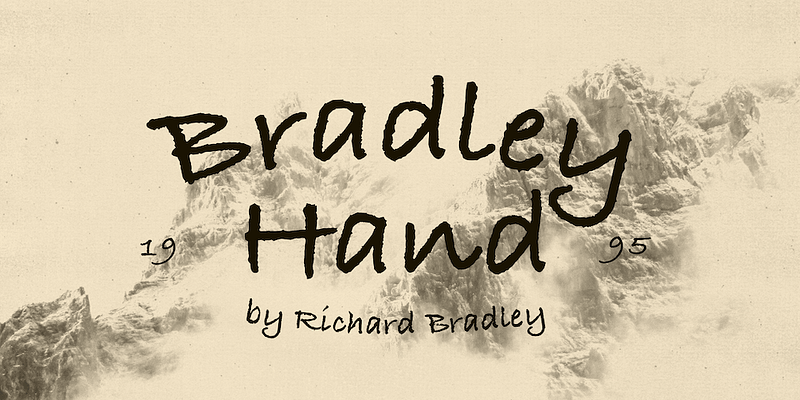
ITC Bradley Hand는 Richard Bradley가 1995년에 디자인한 붓글씨 서체입니다. 거친 종이에 펠트 펜으로 손글씨를 쓴 듯한 윤곽선을 가지고 있으며, 손글씨 특유의 섬세한 디테일이 반영되어 있습니다. 전체적으로 균형 있고 조화로운 인상을 주며 개인적인 감성을 더해줍니다. Bradley Hand는 8pt 정도의 작은 글자 크기에서도 뛰어난 가독성을 유지하며, 헤드라인이나 짧은 문장, 중간 길이의 텍스트에 사용하기에 적합합니다.